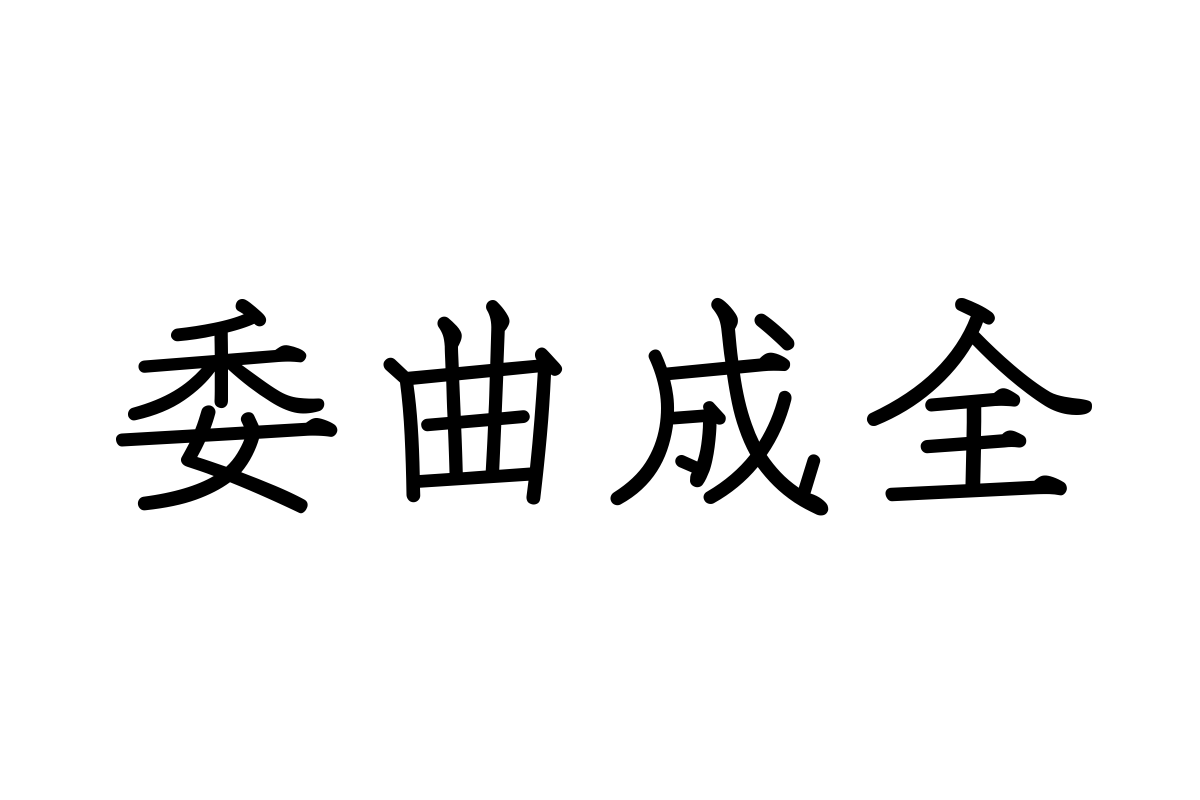
汉仪花冠55W是一款由汉仪公司设计制作的中文字体,具有独特的风格和特点。这款字体采用了现代的设计元素,线条流畅,形状优美,适合用于各种需要美观的文字表达场景。
汉仪花冠55W的特点主要体现在以下几个方面:
1. 字形美观:这款字体的字形线条优美,形状独特,给人一种视觉上的享受。无论是在标题、正文还是装饰性文字中,都能展现出独特的美感。
2. 易读性强:汉仪花冠55W的字形结构清晰,笔画简洁明了,使得阅读起来更加轻松易懂。这对于需要大量文字输入的场景来说,是一个很好的选择。
3. 适应性强:这款字体适用于各种类型的文字表达,无论是正式的文件、报告,还是广告、宣传等场合,都能很好地适应。
总之,汉仪花冠55W是一款非常优秀的中文字体,无论是在设计、制作还是阅读方面,都能给用户带来愉悦的体验。